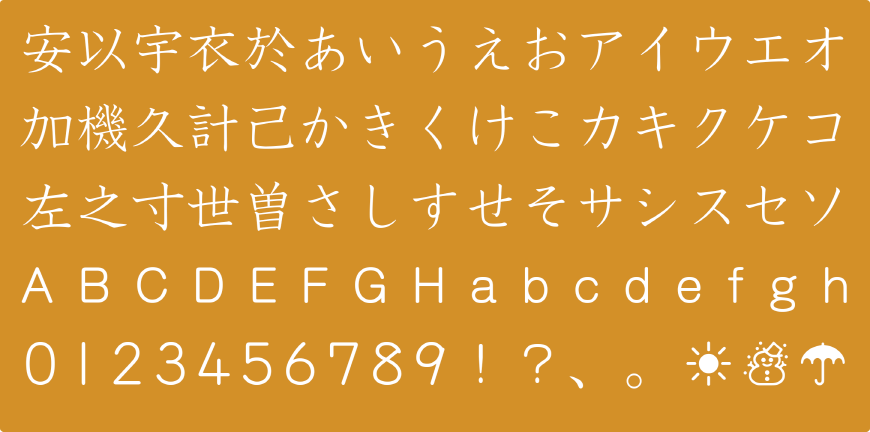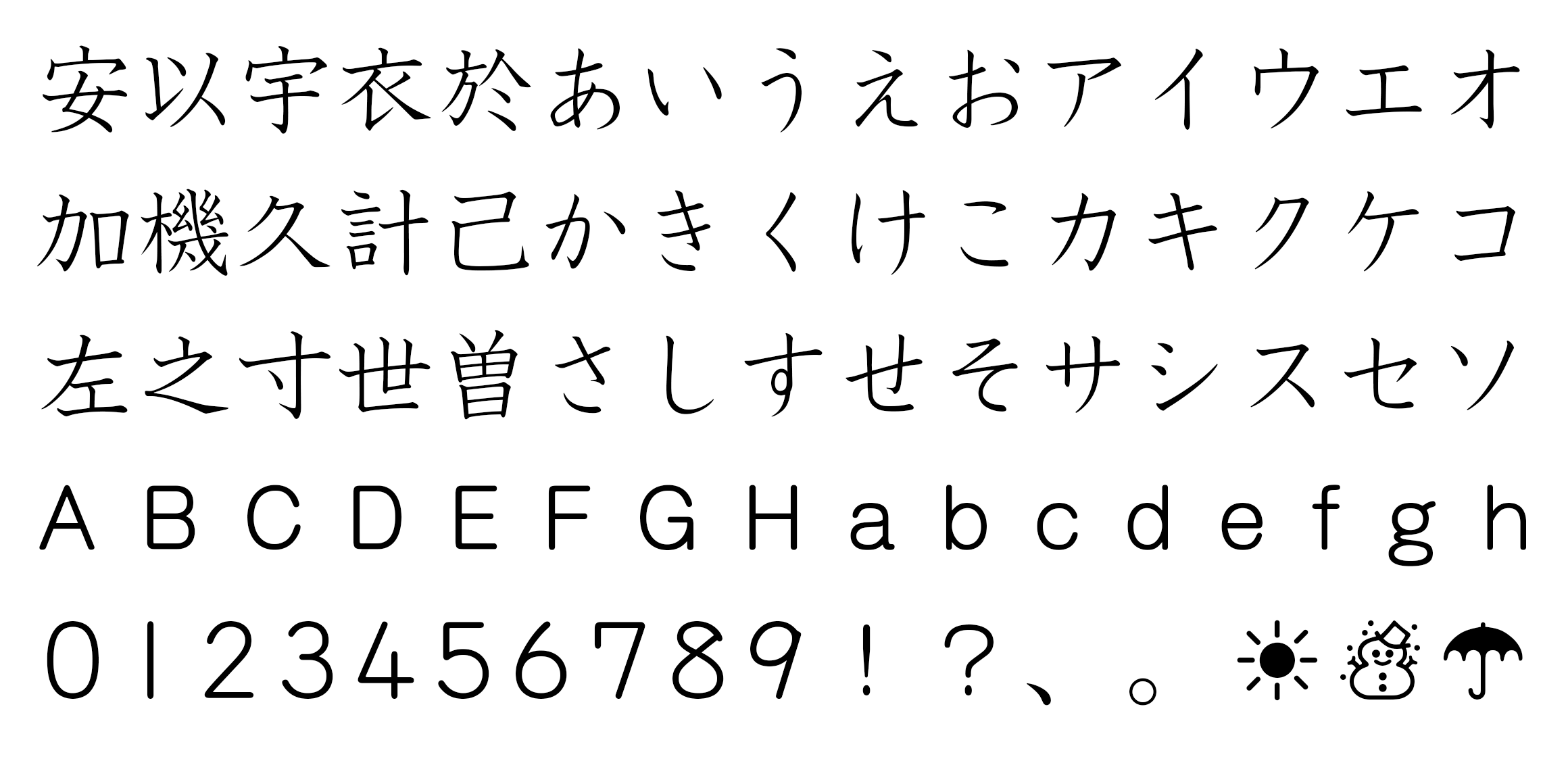
MotoyaKoin
MotoyaKoin(古印体)는 인장(印章) 사용을 염두에 두고 제작된 붓글씨 폰트입니다. 우아하고 부드러운 분위기와 강인함을 겸비하고 있어 실용성 있는 폰트로 완성되었습니다. 인장을 비롯해 웹이나 게임에서의 공포감 연출, 음식점, 잡화점, 고(古)미술품점 등 각종 점포의 간판이나 상품 설명, 온천, 여관, 민박의 현판, 의약품 관련, 과자, 조미료의 각종 패키지, 로고 등 다양한 장르에 사용할 수 있습니다.